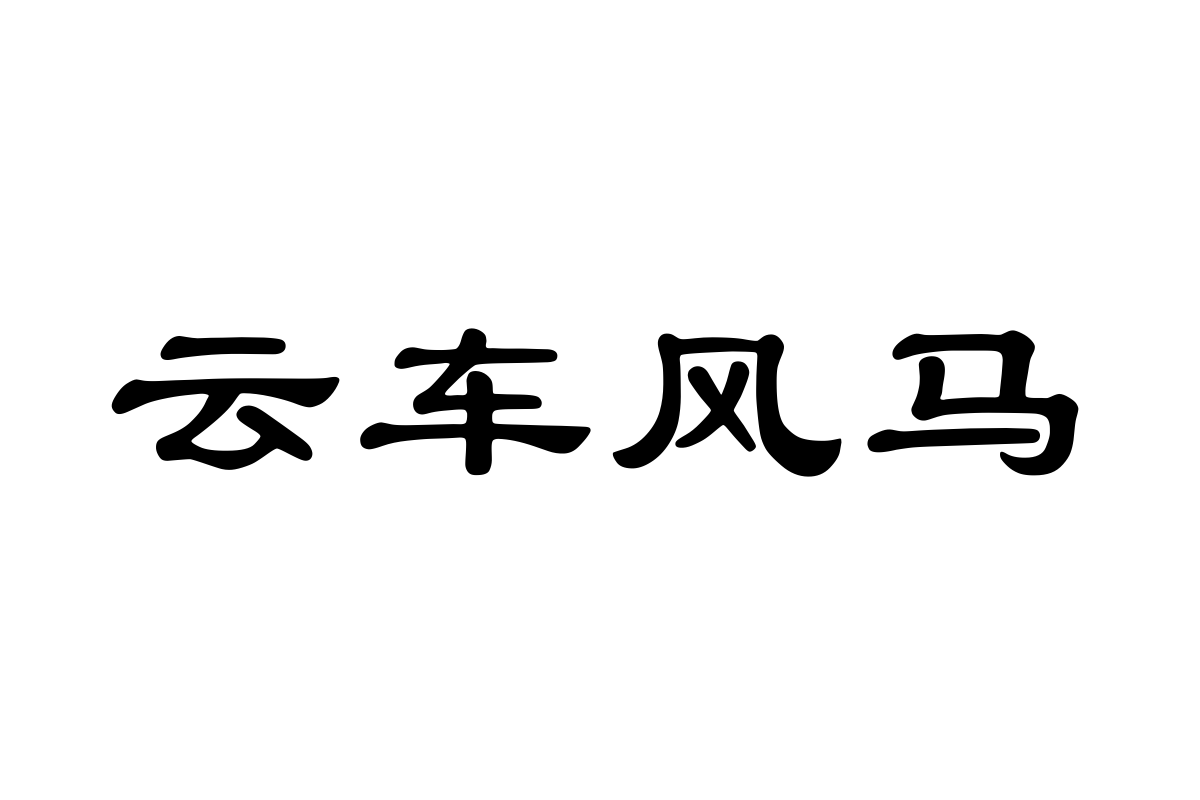
汉仪大隶书简是一款现代字体,由汉仪字库出品。这款字体具有独特的风格和特点,适用于各种设计场景。以下是对汉仪大隶书简字体的详细介绍:
1. 设计风格:汉仪大隶书简字体采用现代简约的设计手法,线条流畅,结构清晰。整体风格庄重大气,适合用于标题、正文等重要场合。
2. 字体结构:该字体由多个笔画组成,每个笔画都有独立的粗细变化。这使得字体在视觉上具有层次感,同时保持了整体的协调性。
3. 字形特点:汉仪大隶书简字体的字形圆润饱满,线条粗犷有力。这种特点使得字体在视觉上具有较强的冲击力和辨识度。
4. 应用场景:这款字体适用于各种商业、广告、宣传等领域的设计。例如,可以用来制作海报、横幅、标志等,能够很好地传达出品牌的形象和信息。
总之,汉仪大隶书简字体是一款现代简约风格的字体,具有独特的设计风格和特点。它适用于各种设计场景,能够满足不同用户的需求。